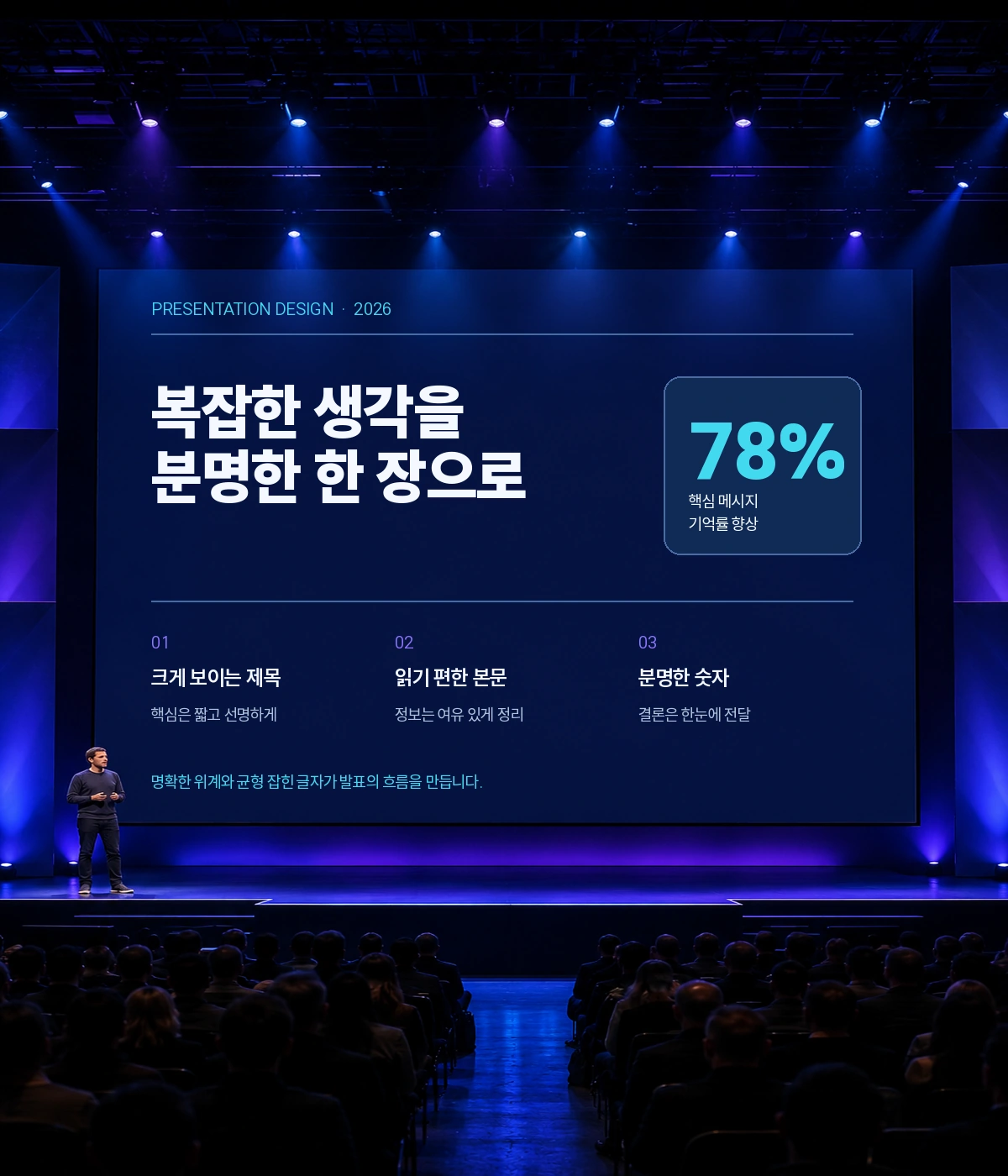
프리젠테이션 — 이주임에서 배포하는 무료 폰트입니다. 디자인을 몰라도 슬라이드가 무너지지 않도록 만든, 발표 화면을 위한 실용적인 본문 서체
18년 동안 프레젠테이션을 만들어 온 디자이너 이주임이 2024년 3월에 내놓은 서체입니다. 내건 문구가 세상에 없던 파워포인트를 위한 폰트이고, 목표는 누구나 막 써도 예쁜 폰트를 만드는 것이었다고 밝히고 있습니다. 디자인을 모르는 사람이 슬라이드를 만들어도 결과물이 무너지지 않게 하겠다는 뜻입니다.
그 목적에 맞춘 결정들이 구체적입니다. 장평을 좁혀 슬라이드 한 장에 더 많은 글자가 들어가게 했고, 자간은 좁히고 행간은 넓혀 손으로 조정하지 않아도 되게 했습니다. 숫자를 고정폭으로 만들어 표에서 소수점과 쉼표가 세로로 맞아떨어지고, 로마숫자는 세리프 형태로 따로 그려 챕터 제목에 쓰도록 했습니다. 도형 안에 글자가 정확히 가운데 오도록 세로 지표까지 맞췄습니다. 한글은 본고딕을, 라틴은 로보토를 바탕으로 다듬었습니다.
굵기는 Thin부터 Black까지 아홉 가지에 가변 폰트가 있습니다. 폰트픽이 서비스하는 판은 현대 한글 11,172자를 모두 담은 쪽입니다. 슬라이드를 겨냥해 장평과 자간을 좁게 잡은 서체라, 반대로 여백이 넉넉해야 하는 인쇄 본문이나 브랜딩 조판에서는 설계 의도와 어긋납니다.